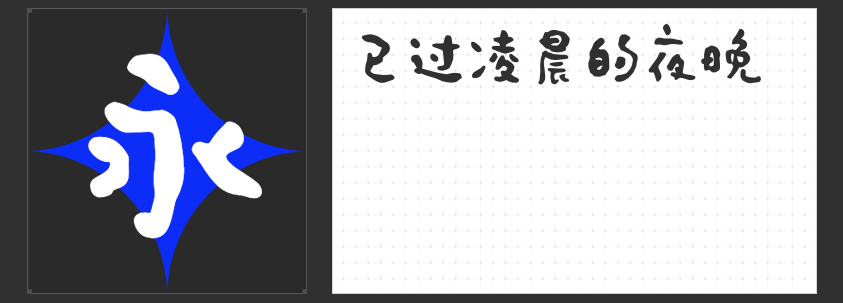
可爱?少女?让这四款字体萌动你心
在打造充满少女心的游戏设计时,选择一款合适的字体往往能为作品增添不少魅力。今天,为大家推荐四款特别适合用于少女心游戏设计的创意字体,它们不仅风格独特,还能让你的游戏更加吸引玩家的目光。
一、字恋狂澄空 絮风
这款字体以手写感为基础,字型上松下紧,重心略低,结构灵活多变,每个字的字面都根据字型结构进行了精心设计,显得灵活有趣。字间距安排合理,组合起来富有节奏感,让文字在游戏界面中显得更加生动。笔画粗细均匀,流畅饱满的弧线与利落的直线相融合,部分笔画折笔处采用平直切角的处理方式,减少了锐度,增加了轻盈感。笔画之间的“断开”处理,更是为字体增添了一份轻快感,非常适合用于打造梦幻、唯美的游戏氛围。
二、字恋狂丸粒简
字型可爱,笔画两端和转折处都进行了圆角处理,使其圆润而富有亲和力。这款字体以其独特的圆润感和亲和力,非常适合用于打造温馨、甜美的游戏场景。无论是游戏内的对话框、提示信息,还是游戏外的宣传海报,都能让玩家感受到满满的少女心。
三、喵字动漫体
喵字动漫体是一款定位动漫风格的字体,整体强调轻微的“律动感”,力求在传统架构的标题字基础上追求“松动”的排版效果。这款字体非常适合用于打造动漫风格的游戏,无论是游戏内的角色名称、技能描述,还是游戏外的宣传文案,都能让玩家感受到浓厚的动漫氛围。
四、字恋狂深夜简繁
这款创意手写体笔触如同蜿蜒曲折的流水,字形散漫扭曲,似被水波荡漾。其独特的笔触和字形设计,非常适合用于打造神秘、浪漫的游戏场景。无论是游戏内的剧情描述、背景设定,还是游戏外的宣传文案,都能让玩家沉浸在这份独特的氛围中。
这四款字体各具特色,无论是手写感、圆润感、动漫风还是独特笔触,都能为你的少女心游戏设计增添不少魅力。快来尝试将它们融入你的游戏作品中吧!